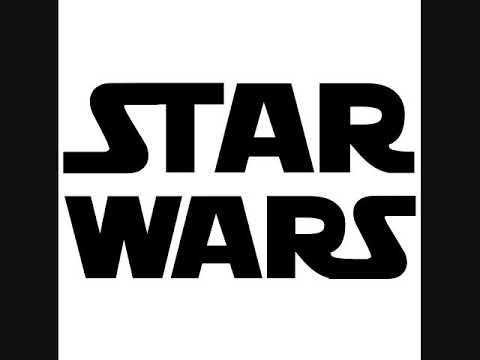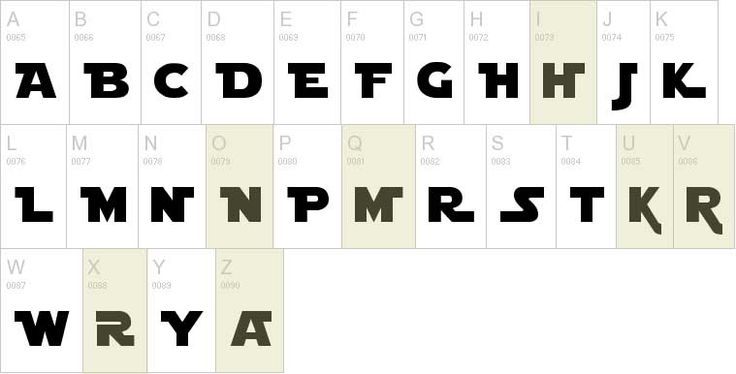
«В эфемерной далекой галактике были несколько вариантов для поклонников этого эпического шоу, когда они искали правильный шрифт для использования в своих проектах.
Вам нужно набраться терпения с молодыми джедаями.
05. Star Jedi Outline
Star Jedi Outline Шрифт star wars можно использовать с другими шрифтами Boba.